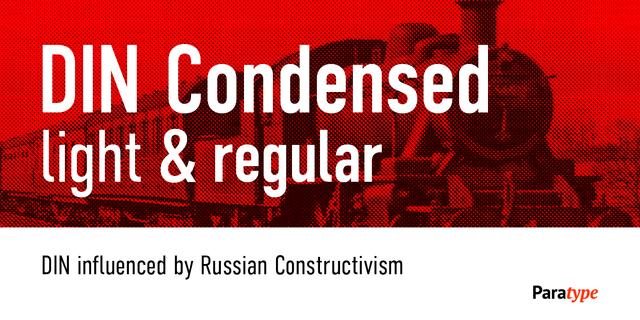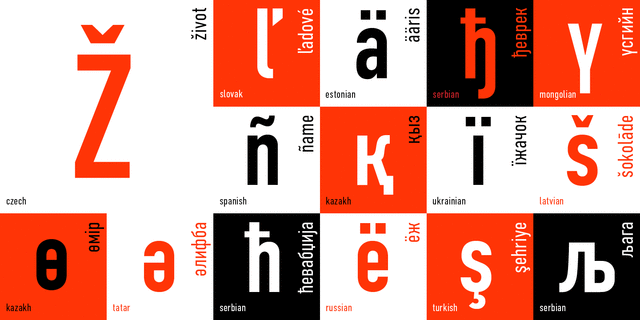
Шрифт разработан в фирме ПараТайп (ПараГраф) в 1997 (дизайнер Тагир Сафаев) на основе рисунков узкого начертания шрифтов DIN, созданных штатными дизайнерами фирмы Linotype. Это геометрические гротески, приспособленные к требованиям немецких промышленных стандартов. Их начертания видоизменяются по ширинам, но сближены по цвету. Светлое начертание добавлено Манвелом Шмавоняном в 2014 году. Полужирное начертание добавлено Изабеллой Чаевой в 2020 году.
точный, ровный, прямоугольный, стабильный, серьезный, надежный, уверенный, устойчивый, техногенный, статичный, авторитетный, убедительный, городской, простой, урбанистический, строгий, деловой, современный, монотонный, логичный, прагматичный, практичный, искусственный, холодный, машинный, инженерный, твердый, сильный, индустриальный, мотивирующий, крутой, железнодорожный, чертежный, урбанистичный, умный, высокий, автоматический, стальной, крепкий, железный, архитектурный, громкий, рабочий, ответственный, промышленный, важный, военный, тяжелый, амбициозный, броский, заметный, мощный, суровый